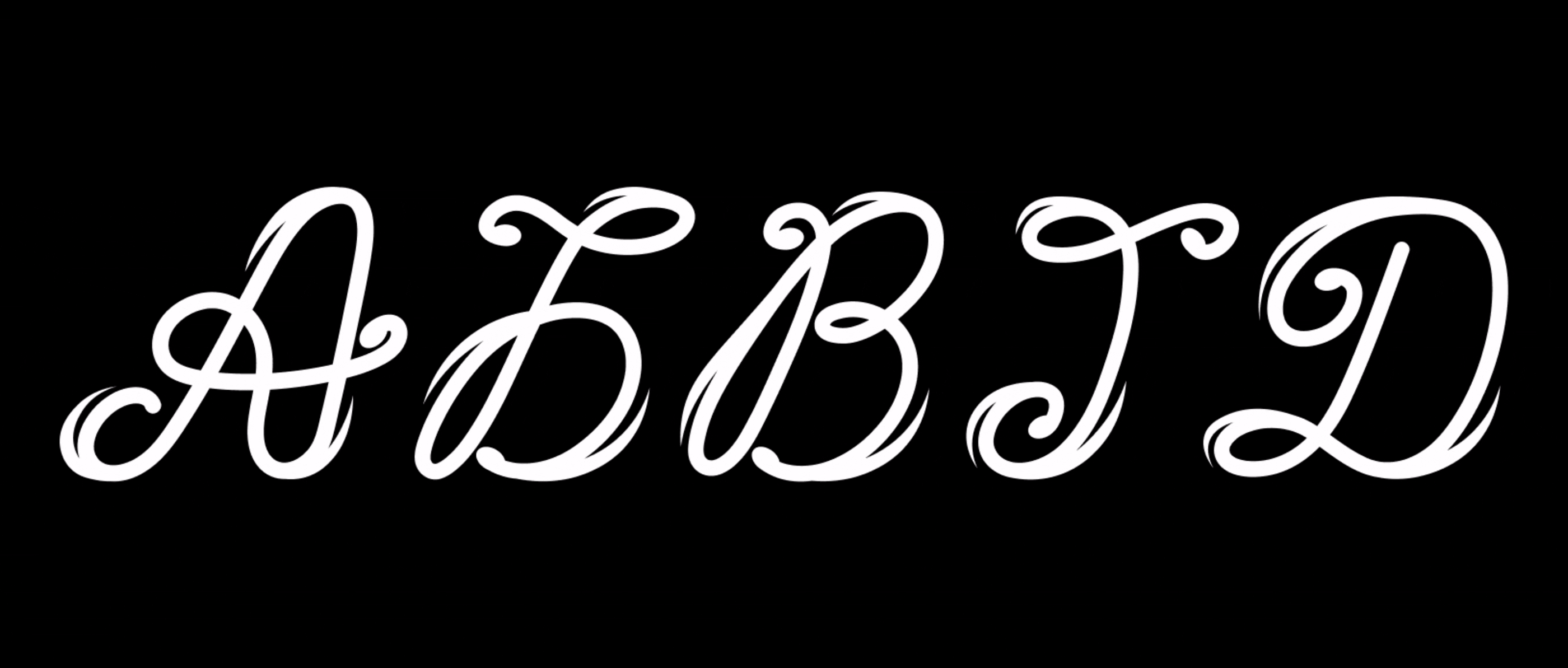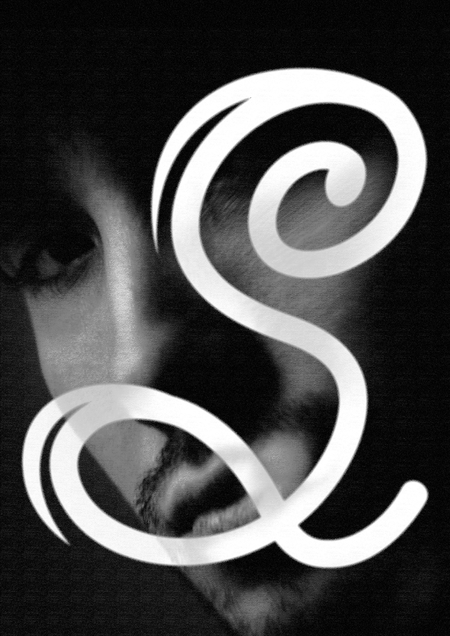
Акцидентный шрифт, создан для музыкального продюсера и исполнителя SouthBoy, работающего в жанре электронной музыки. В основу шрифта легли башкирские составные орнаменты, что отсылает к родному городу артиста — Уфе.